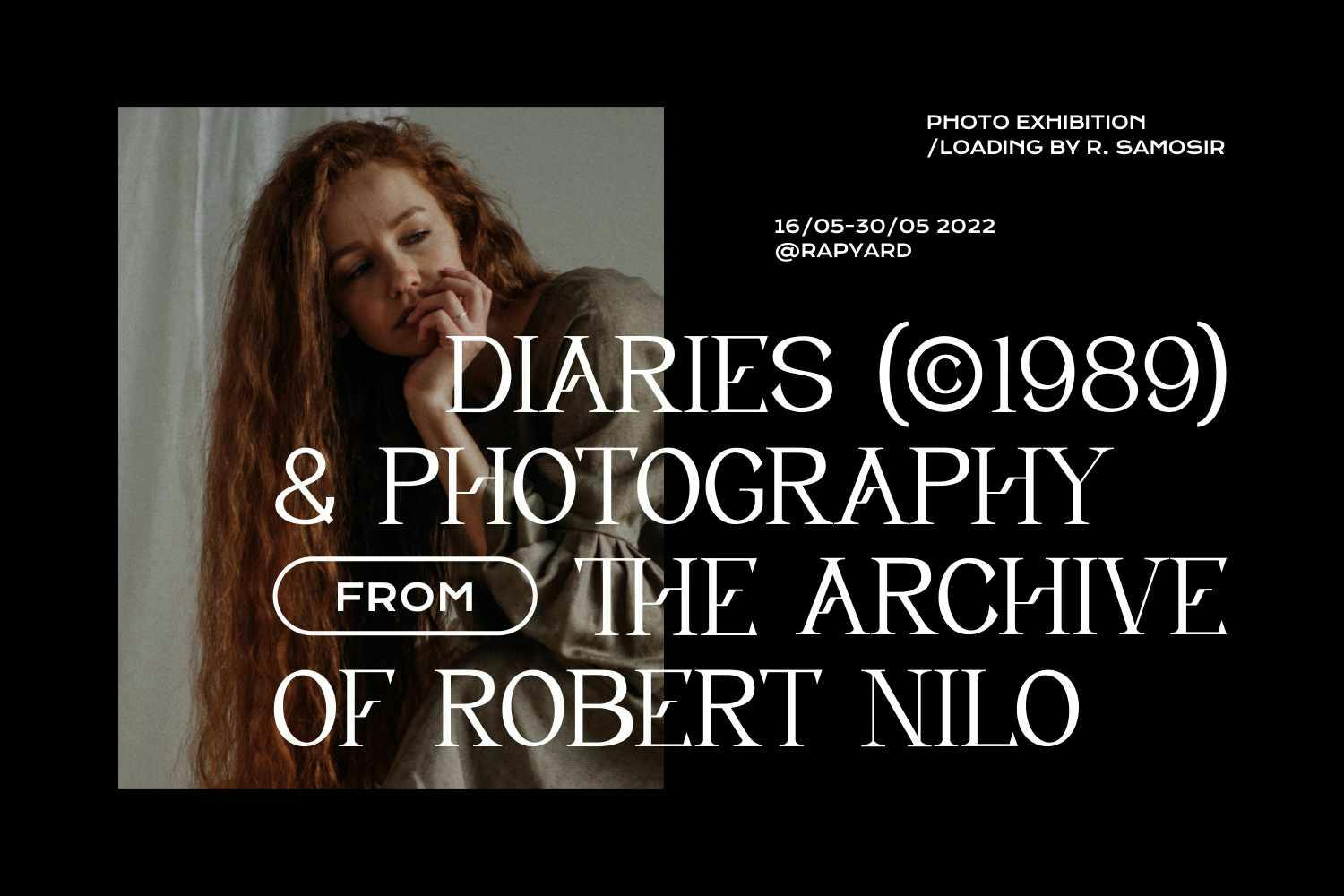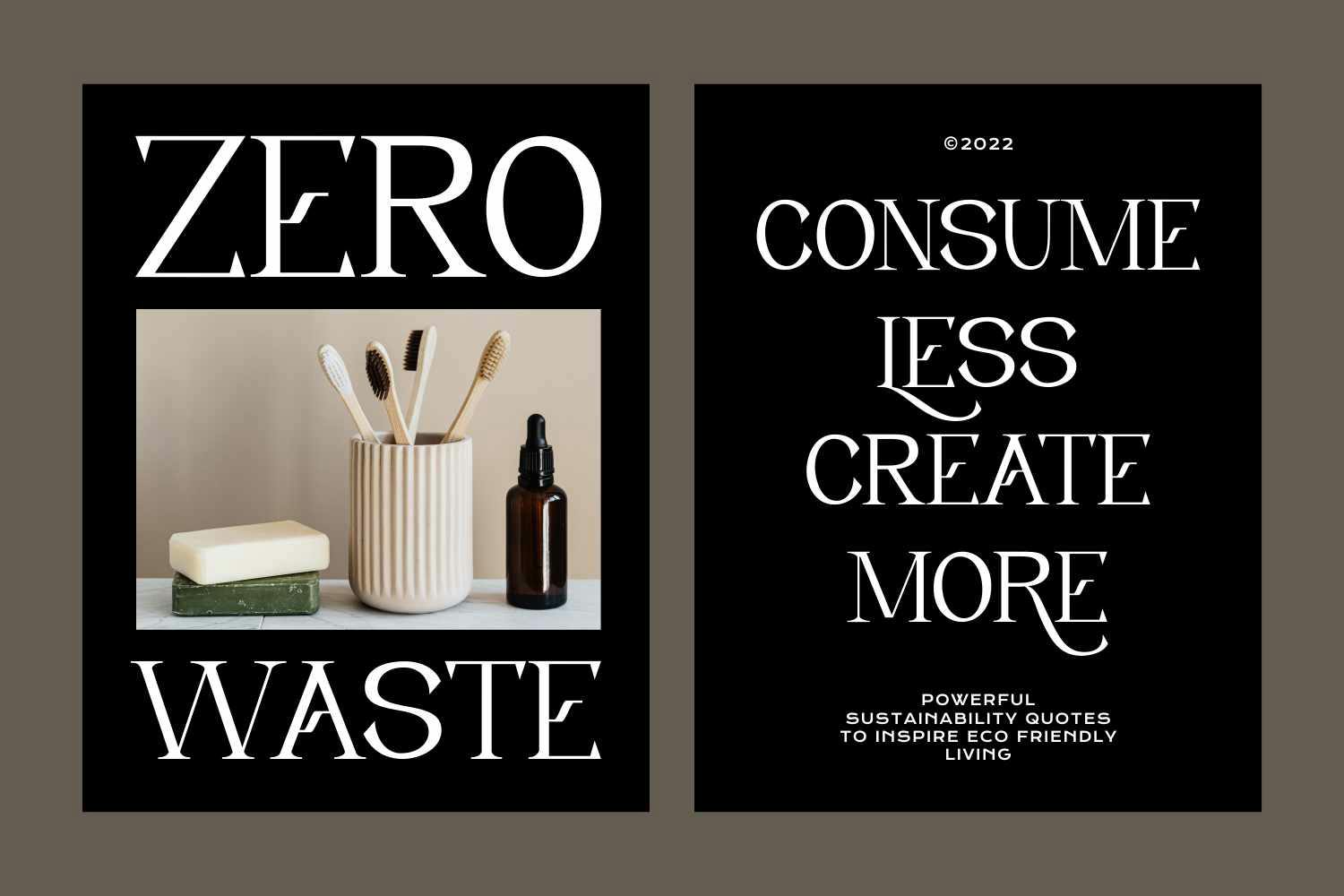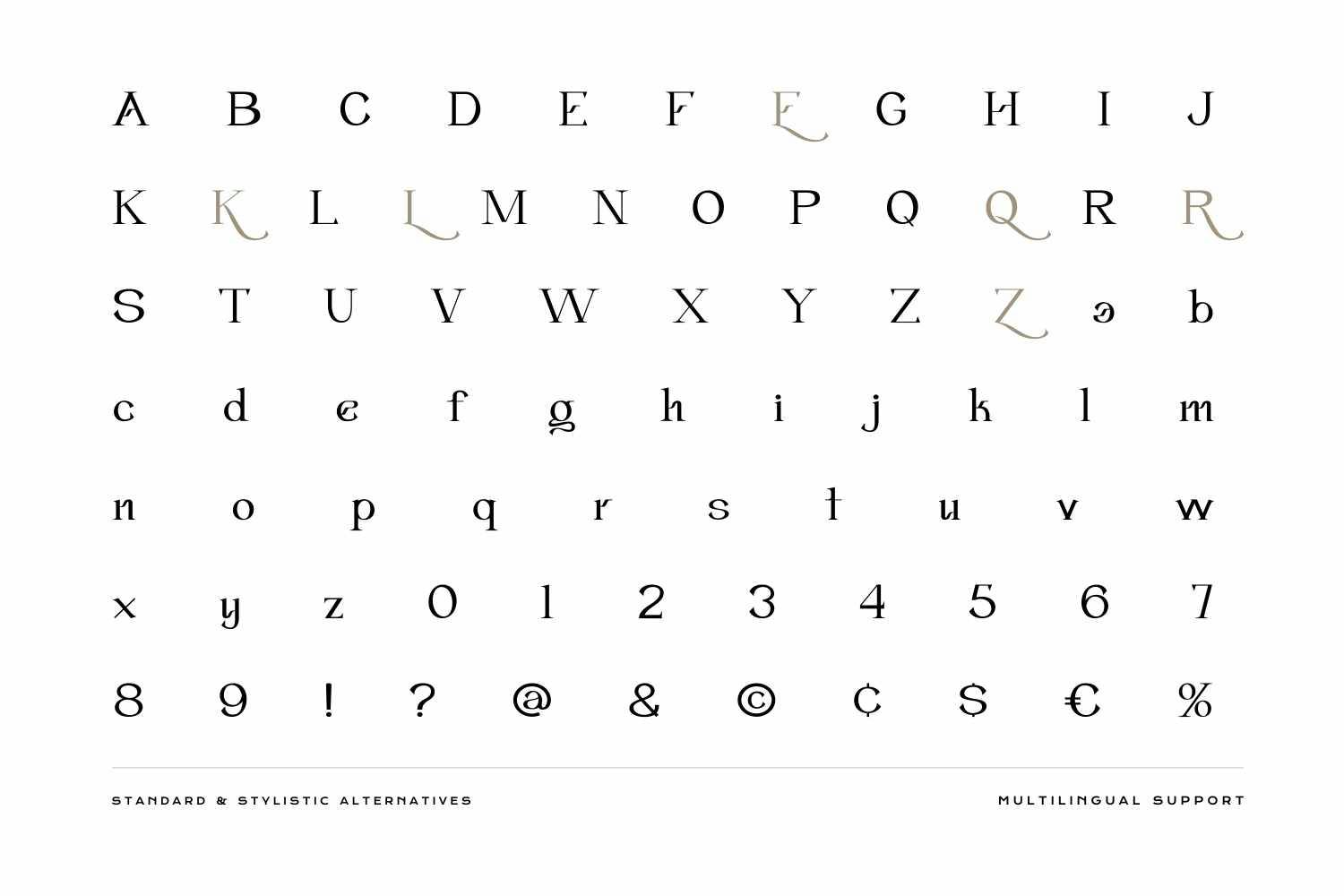
فونت Vaimek یک انتخاب مناسب برای برندینگ، کتاب، لوگو، مجله، محصولات مد، نقلقولها، پوسترها، سرصفحهها و غیره است. این فونتها دارای حروف بزرگ و کوچک، اعداد و نشانهها، پشتیبانی چند زبانه و ویژگیهای OpenType هستند. برای طراحیهای شگفتانگیز میتوانید با دیگر فونتها ترکیب کنید تا به عنوان مکمل استفاده شوند.